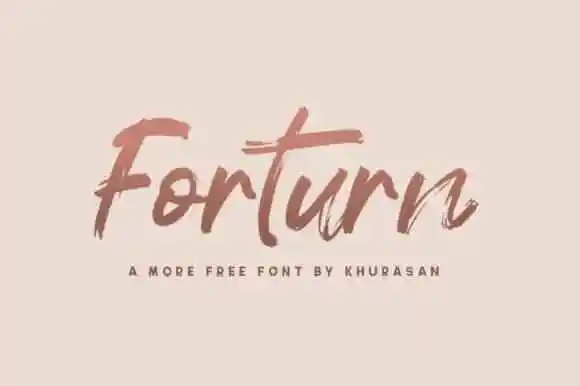
Forturn Brush Font – Download Grátis
Forturn Brush Font é uma tipografia feita à mão que transmite uma sensação relaxada e fluída. Manufacturada pela Khurasan, essa fonte apresenta incrível versatilidade, adequando-se a um vasto leque de designs. Seu equilíbrio e arredondamento em harmonia tornam-a perfeita para aumentar o valor desses projetos. Forturn Brush é especialmente indicada para aplicações como anúncios, logos e identidade visual, ou qualquer design que precise de um aspecto atraente e inovador. Suas linhas fluidas e suaves oferecem uma solução perfeita para aqueles desejando adicionar estilo ao seu trabalho. É uma fonte ideal tanto para iniciantes quanto para profissionais, proporcionando flexibilidade e criatividade sem comprometer o resultado final. Seja você um designer de gráficos, um especialista em branding ou um entusiasta do design, Forturn Brush é uma escolha inteligente que certamente valorizará seu trabalho.